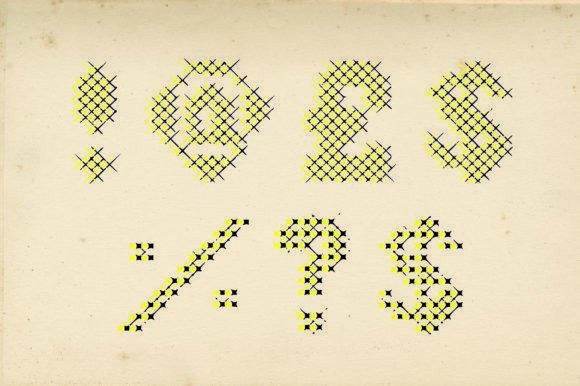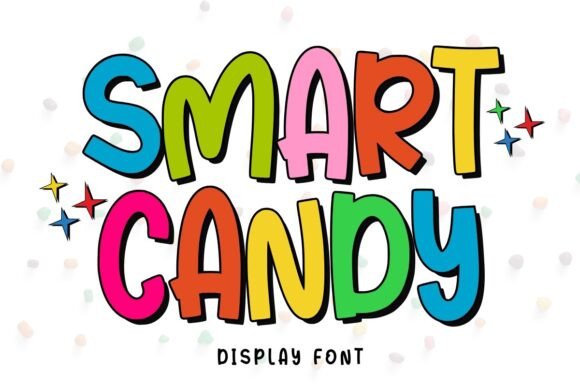
SVG Crafting Font Bundle Sweet Home
Het vinden van de juiste ontwerpelementen kan lastig zijn, maar SVG Crafting Font Bundle Sweet Home biedt een uitzonderlijke collectie die uw werk direct naar een hoger niveau tilt.
Met precisie gemaakt, biedt SVG Crafting Font Bundle Sweet Home strakke vectoren, vloeiende typografie en een commerciële licentie voor uw gemoedsrust.